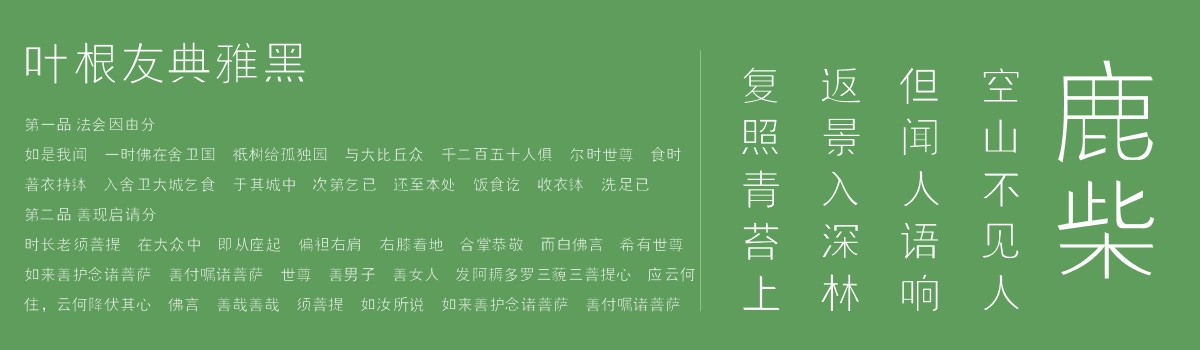
叶根友典雅黑
字体作者:叶根友
创作年代:2013年
字体字数:6763个中文汉字以及其他英文字母和阿拉伯数字
字体适合:内文排版或手机应用
字体介绍
叶根友典雅黑是一款正规的黑体类型的字体,是微黑字体的风格借鉴版,字型干练利落,具有时代鲜明特点,线条流动韵律之书法风格的美中透露出一种锐气,起笔落笔间的15度斜角,让字的展现更具时代特征,适合用于内文排版字体。
风格展示